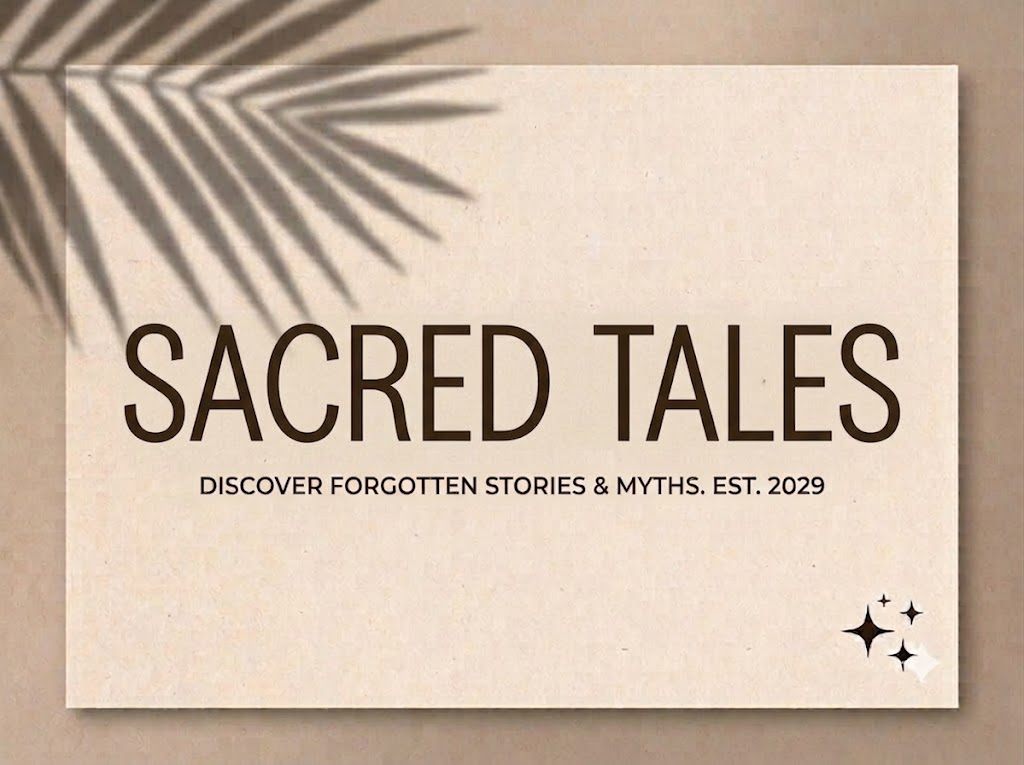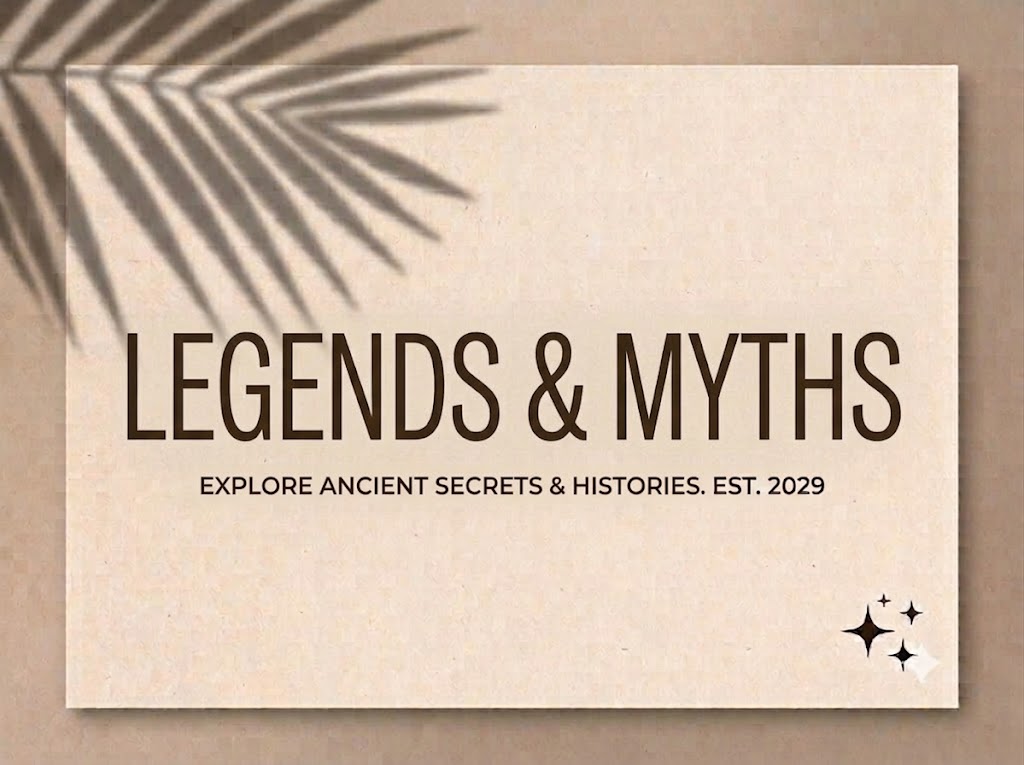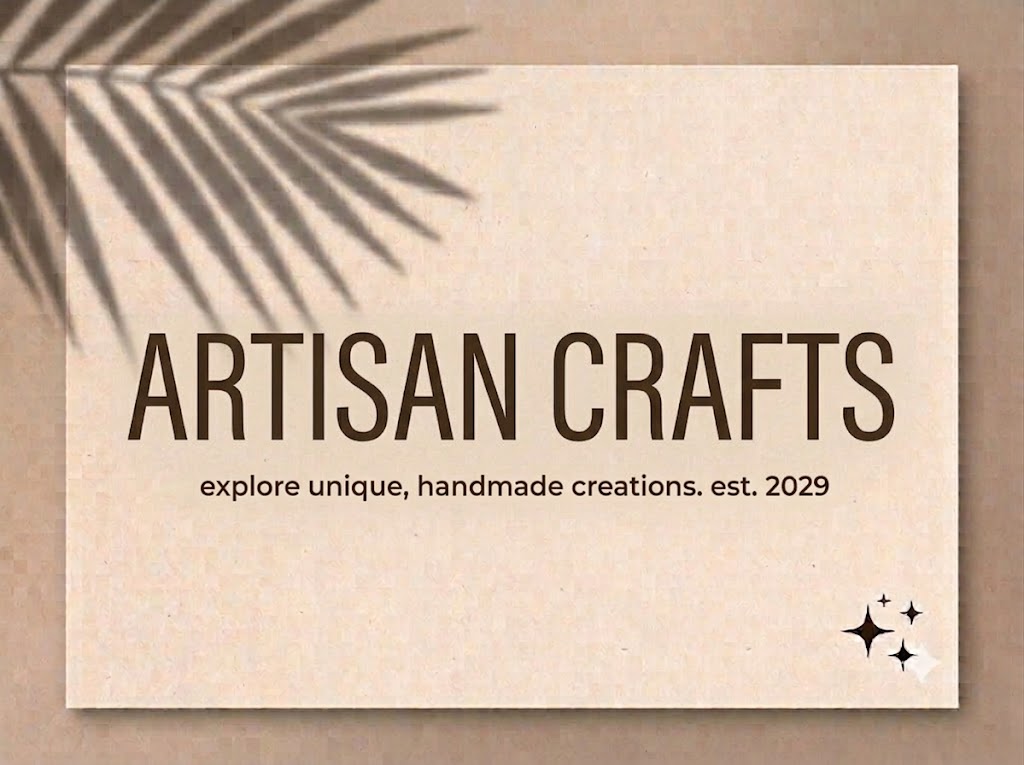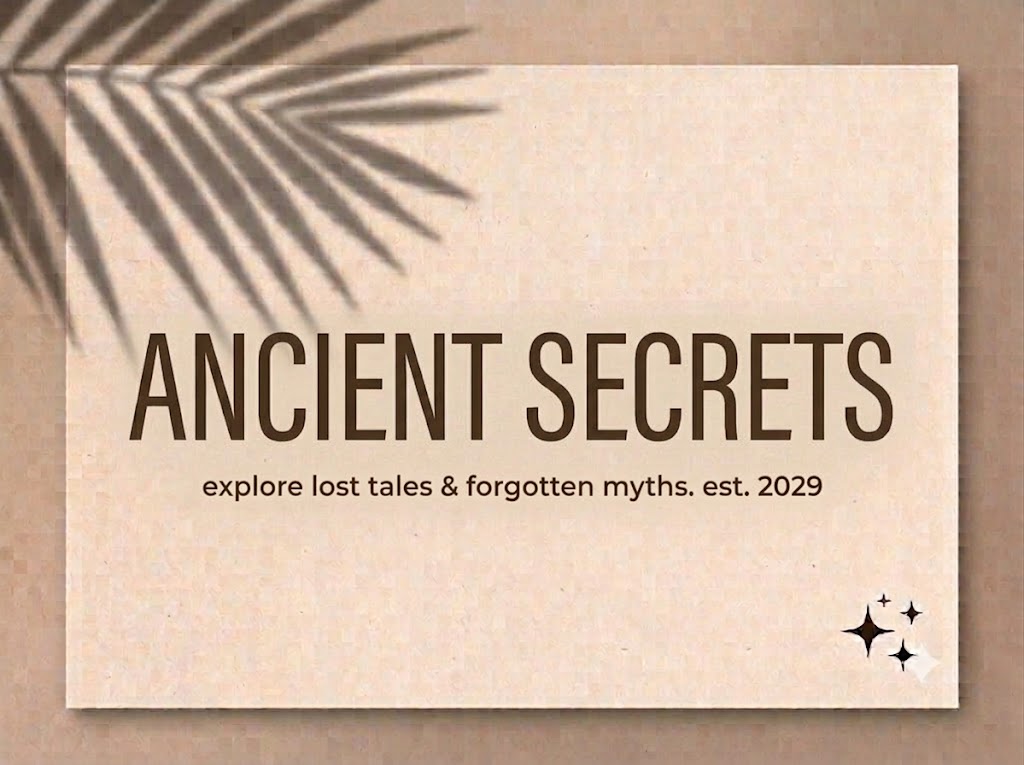
1FTV Gasket
Trong kỷ nguyên số, khi xu hướng lướt nội dung trên các thiết bị di động ngày càng chiếm ưu thế, việc tối ưu hóa không gian hiển thị của chữ viết trở thành một bài toán sống còn đối với các nhà thiết kế.
Những dòng phông chữ thuộc nhóm condensed (dáng cao, thuôn hẹp) chính là vũ khí bí mật giúp giải quyết triệt để vấn đề này, vừa đảm bảo chứa đựng trọn vẹn thông điệp ngắn gọn, vừa mang lại cấu trúc thị giác vô cùng gọn gàng, tinh tế.
Nếu bạn đang tìm kiếm một bộ chữ không chân dáng đứng hiện đại, vừa mang hơi hướng kỹ thuật công nghiệp lại vừa có tính ứng dụng cực cao, thì font 1FTV Gasket chính là câu trả lời lý tưởng.
Giới thiệu về font 1FTV Gasket
Font 1FTV Gasket là một bộ chữ hiển thị và văn bản không chân (sans-serif) được thiết kế theo phom dáng condensed thanh lịch, gọn gàng và mang tính thực tế rất cao.
Tác phẩm này được hoàn thiện đồng bộ ở phiên bản Version 1.000, đem lại kết cấu đường nét vô cùng tinh tế và mượt mà cho từng chữ cái khi sắp xếp cạnh nhau.
Nhờ những thông số kỹ thuật tối ưu này, phông chữ hiển thị vô cùng sắc nét trên mọi phần mềm biên tập đồ họa hiện đại mà không gặp phải tình trạng răng cưa hay vỡ nét khi bạn phóng to thu nhỏ.
Đặc điểm nổi bật của phong cách thiết kế Gasket
Sức hút lớn nhất của font 1FTV Gasket đến từ cấu trúc hình khối condensed thuôn dài theo chiều dọc kết hợp cùng các nét chữ vuông vắn, dứt khoát.
Tên gọi “Gasket” (vòng đệm kỹ thuật) phần nào phản ánh tinh thần của bộ chữ: sự chính xác, vừa vặn, kiên cố và mang đậm hơi thở của ngành cơ khí công nghiệp hiện đại.
Khác với nhiều dòng font display chỉ hỗ trợ chữ viết hoa, 1FTV Gasket tích hợp trọn vẹn cả hệ thống chữ cái thường lẫn chữ viết hoa đồng bộ. Điều này mang lại sự linh hoạt tối đa khi sắp xếp bố cục văn bản, giúp các tầng nội dung (tiêu đề chính, tiêu đề phụ) được phân tách rõ ràng và tự nhiên.
Độ dày nét chữ ở mức vừa phải (regular đến semi-bold), khoảng trống bên trong ký tự (counter) được tính toán khoa học, giúp khối chữ luôn thanh thoát, thoáng mắt và giữ được độ thẩm mỹ cao.
Hệ thống khoảng cách chữ (kerning) và độ giãn dòng đã được căn chỉnh chuẩn xác, giúp các từ khi đứng cạnh nhau luôn giữ được sự liền mạch mà không bị dính nét hay gây cảm giác ngột ngạt.
Bên cạnh hệ thống chữ cái hoa và thường đồng bộ, phông chữ còn tích hợp đầy đủ dãy số từ 0-9 cùng hệ thống các ký tự đặc biệt, dấu câu thông dụng (1234567890.:,;'"(!?)+-*/=).
Đặc biệt, bản Việt hóa chuẩn chỉnh này giúp bạn hoàn toàn yên tâm thiết kế các văn bản tiếng Việt có dấu mà không lo gặp phải tình trạng lỗi hiển thị, nhảy font hay thiếu ký tự khi gõ.
Hình ảnh demo thực tế của font 1FTV Gasket
Kích thước nhỏ (12pt – 24pt): Nhờ dáng chữ cao thuôn gọn, các nét chữ và bộ chữ thường vẫn hiển thị rất rõ ràng, ngay ngắn, cực kỳ dễ đọc ngay cả trên màn hình điện thoại di động cỡ nhỏ.
Kích thước lớn (36pt – 72pt): Đây là không gian lý tưởng nhất để font phô diễn toàn bộ sự chắc chắn, tinh tế của cấu trúc hình khối, tạo hiệu ứng thị giác gọn gàng cho các tiêu đề chính.
Ứng dụng của font Gasket trong thiết kế đồ họa và làm video
Sở hữu nét cá tính tối giản, kỹ thuật và cấu trúc hoa – thường linh hoạt, font 1FTV Gasket mở ra không gian ứng dụng vô cùng rộng lớn cho các dự án truyền thông và marketing:
Làm tiêu đề và phụ đề cho video ngắn (TikTok, Reels, Shorts): Dáng chữ condensed thuôn gọn dọc cực kỳ hoàn hảo cho khung hình đứng 9:16, giúp bạn chèn các câu giật tít dài vào không gian hẹp của màn hình điện thoại mà không lo bị tràn viền hay che mất chủ thể video.
Thiết kế Catalogue kỹ thuật và sản phẩm: Phù hợp làm phông chữ tiêu đề, thông số kỹ thuật cho các catalogue sản phẩm cơ khí, thiết bị phần cứng, máy móc công nghiệp nhờ vẻ ngoài chính xác, chuyên nghiệp.
Ảnh thu nhỏ YouTube (Thumbnail) và Banner quảng cáo: Thích hợp cho các nội dung thuộc chủ đề công nghệ, review đồ điện tử, chia sẻ kiến thức, giáo dục hoặc các chiến dịch quảng cáo cần sự súc tích, trực diện.
Nhận diện thương hiệu phong cách hiện đại: Phù hợp làm logo dạng chữ khối, biểu ngữ quảng cáo hoặc thiết kế nhãn mác cho các thương hiệu thời trang tối giản, kiến trúc, hay các công ty khởi nghiệp công nghệ.